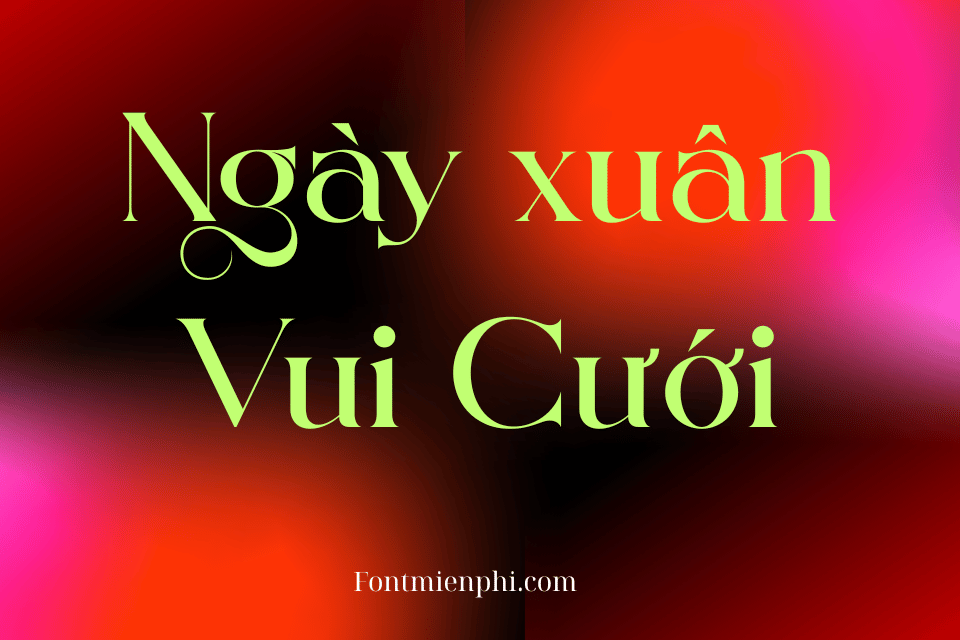
Font Việt hóa 1FTV VIP Gerlomi ,font Tết
Font Việt Hóa 1FTV VIP Gerlomi – “Đắt Nét Xuân” Cho Thiết Kế Tết
Đặc điểm nổi bật:
• Kiểu chữ bay bổng, thanh lịch: Nét mảnh kết hợp hoa văn Tết truyền thống (cành đào, lá mai, họa tiết lụa).
• Tối ưu cho tiếng Việt: Full bộ dấu, hỗ trợ đa dạng font weight (từ Light đến Bold).
• Chất VIP: Phủ vàng/đỏ trong bản Pro, dễ dàng blend màu với background Tết.
Ứng dụng “hot” Tết 2025:
• Thiệp chúc mừng, banner “Lộc Xuân Thịnh Vượng”.
• Poster quảng cáo Tết (rượu bia, bánh mứt, hàng cao cấp).
• Profile công ty phiên bản Tết (dành cho đối tác).
“Gerlomi không chỉ là font – là tinh hoa Tết trong từng nét chữ!”